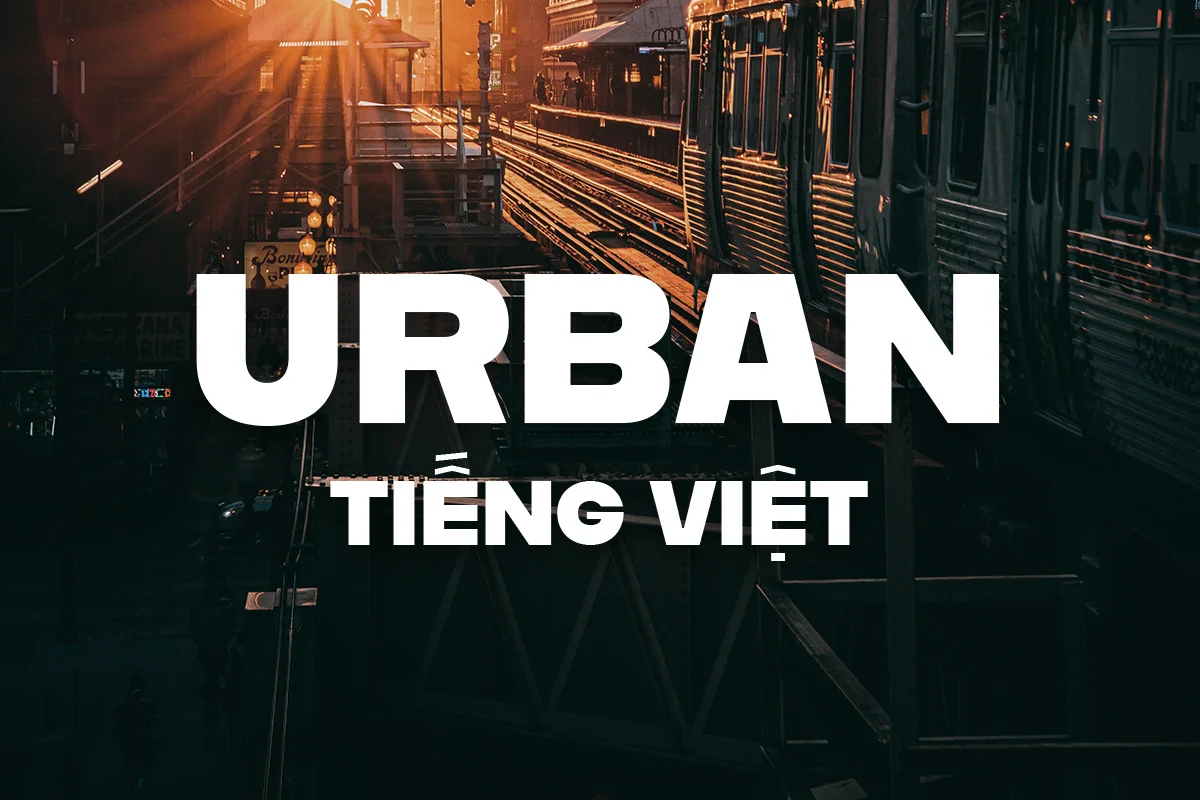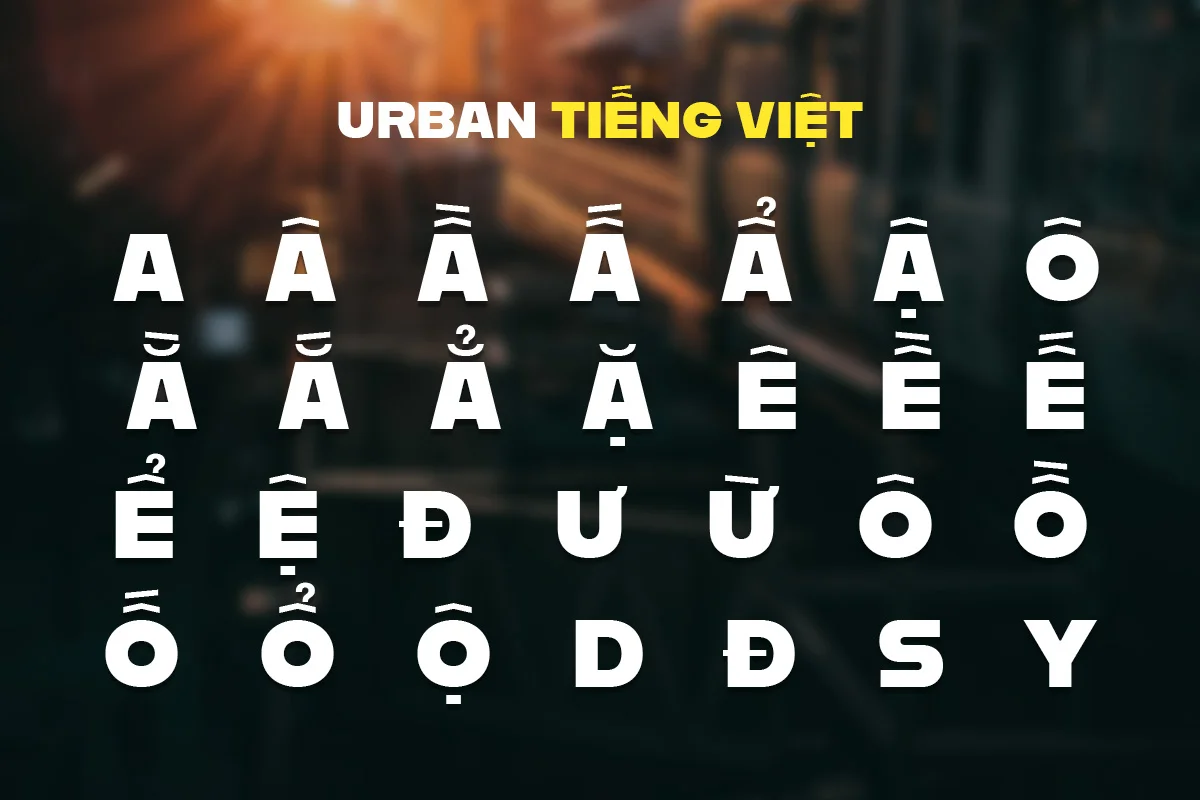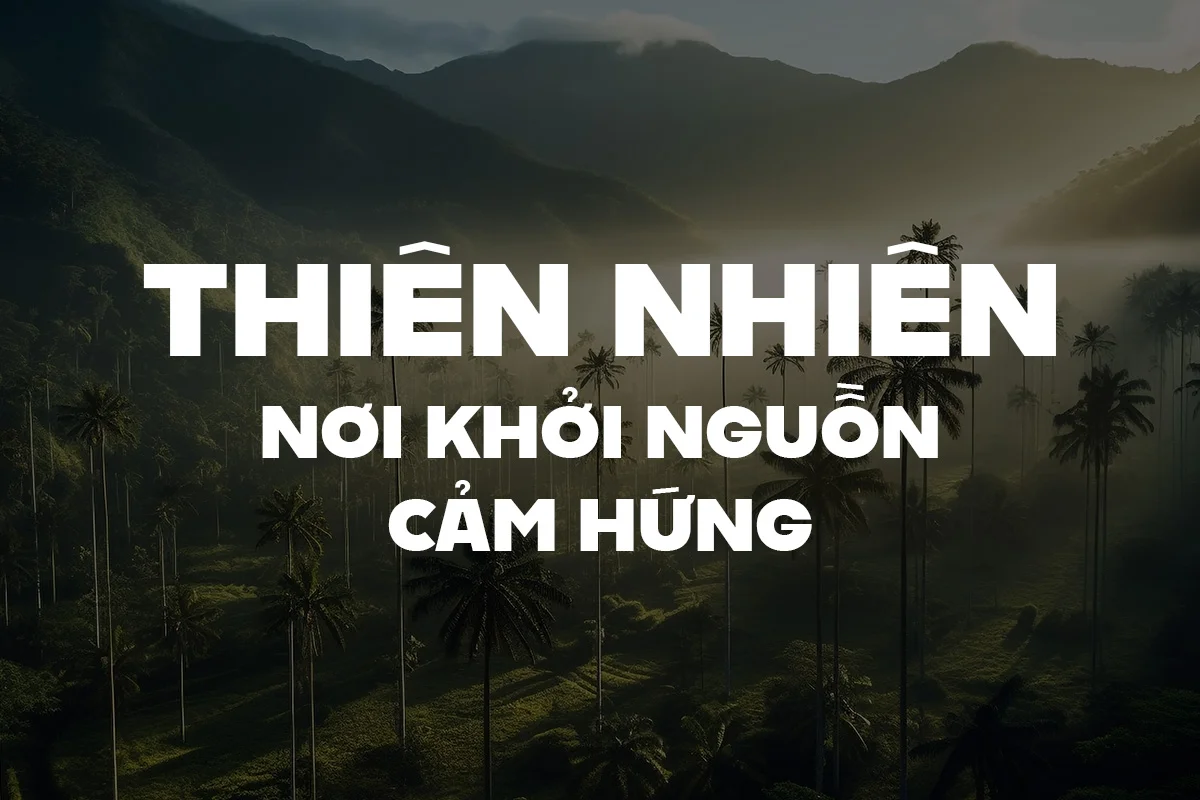
DVN Urban là một kiểu chữ sans serif tiếng Việt với thiết kế dày dặn, vuông vức và chắc chắn. Font mang đến cảm giác mạnh mẽ, trực diện và hiện đại, phù hợp với tinh thần đô thị – công nghệ – sáng tạo trẻ.
Nhờ sự tối giản nhưng giàu ấn tượng, DVN Urban rất thích hợp cho tiêu đề, poster, banner quảng cáo, nhận diện thương hiệu và các ấn phẩm truyền thông cần sự nổi bật. Font hỗ trợ đầy đủ dấu tiếng Việt, giúp nhà thiết kế dễ dàng ứng dụng trong nhiều ngữ cảnh sáng tạo khác nhau.